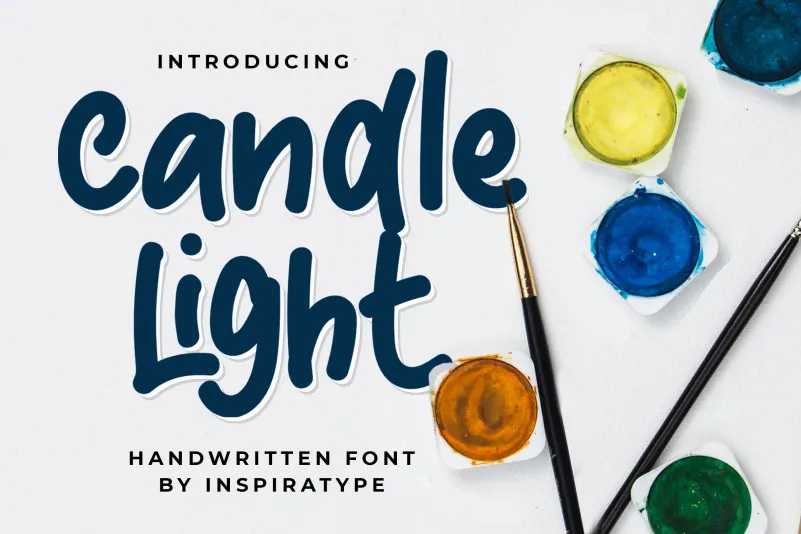
Candle Light – Handwritten Font – Download Grátis
Candle Light – Handwritten Font é uma exuberante fonte de display inspirada no estilo dos anúncios clássicos. Ela surge diretamente do papel, criando uma atmosfera envolvente e natural que combina elementos elegantes com um toque romântico. Inspiradas em cartazes de época, esta fonte oferece uma opção divertida para quem busca adicionar um pouco de brilho e charme a qualquer projeto. Seja ela o rosto de seu próximo site ou o título de sua próxima publicação de blog, Candle Light – Handwritten Font trará vida e personalidade ao design. Perfect para aqueles buscando uma fonte elegante que também tem um toque nostálgico, esta é definitivamente a escolha perfeita. Inspirasign, designer por trás desta criação artística, oferece mais ainda em sua vasta gama de recursos gráficos, cada detalhe meticulosamente cuidado para proporcionar uma experiência única e memorável.